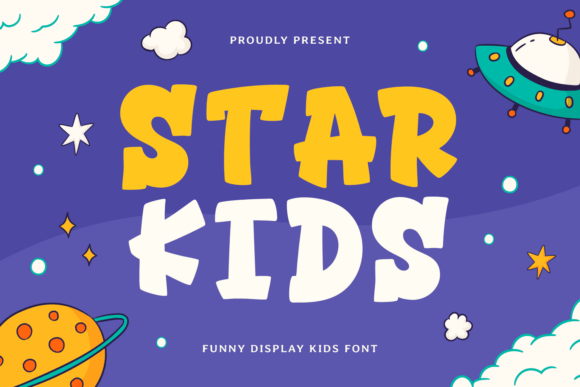
Starkids
Encontrar los elementos de diseño adecuados puede ser un desafío, pero Starkids ofrece una colección excepcional que eleva tu trabajo al instante.